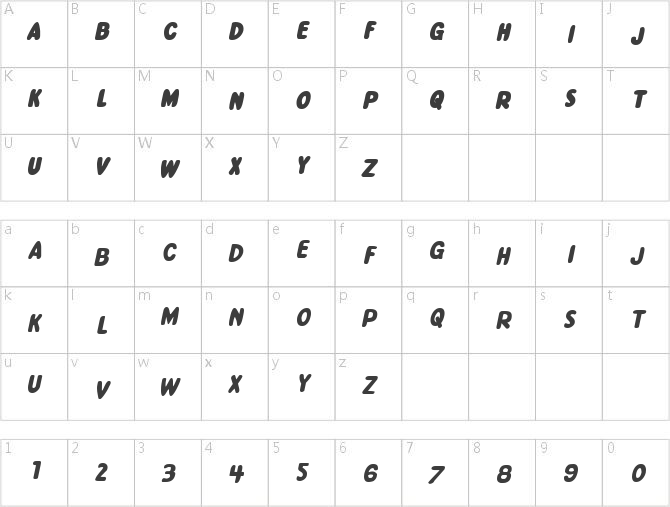
excelsiorcomicsexpandital 詳情頁
excelsiorcomicsexpandital
excelsiorcomicsexpandital字體字庫是一款讓人賞心悅目、百看不厭的英文字體,適合各類廣告和產品包裝設計應用,字體大小0.05MB,格式為ttf字體,上傳用戶是woslxn,作者/版權方為未知